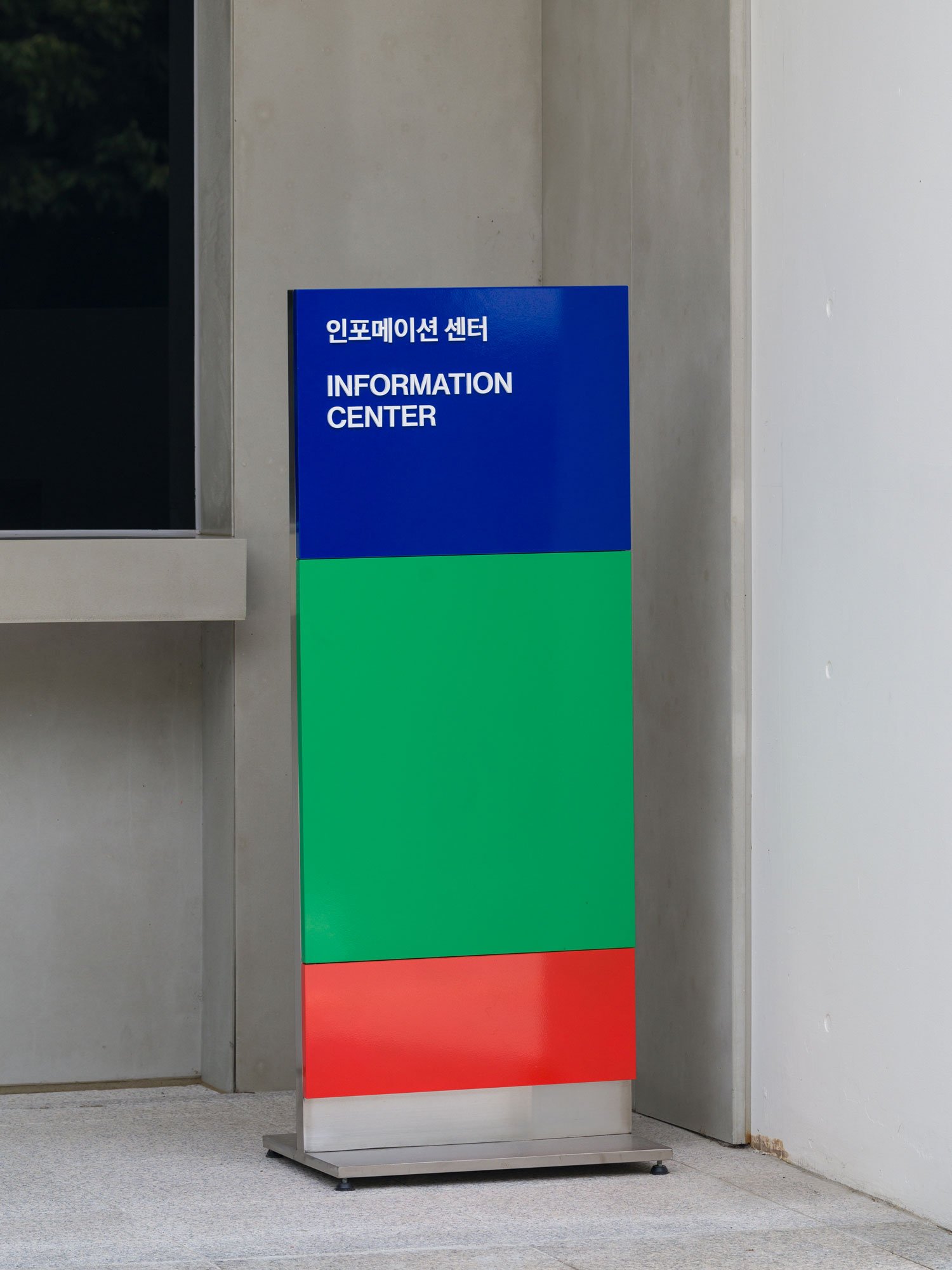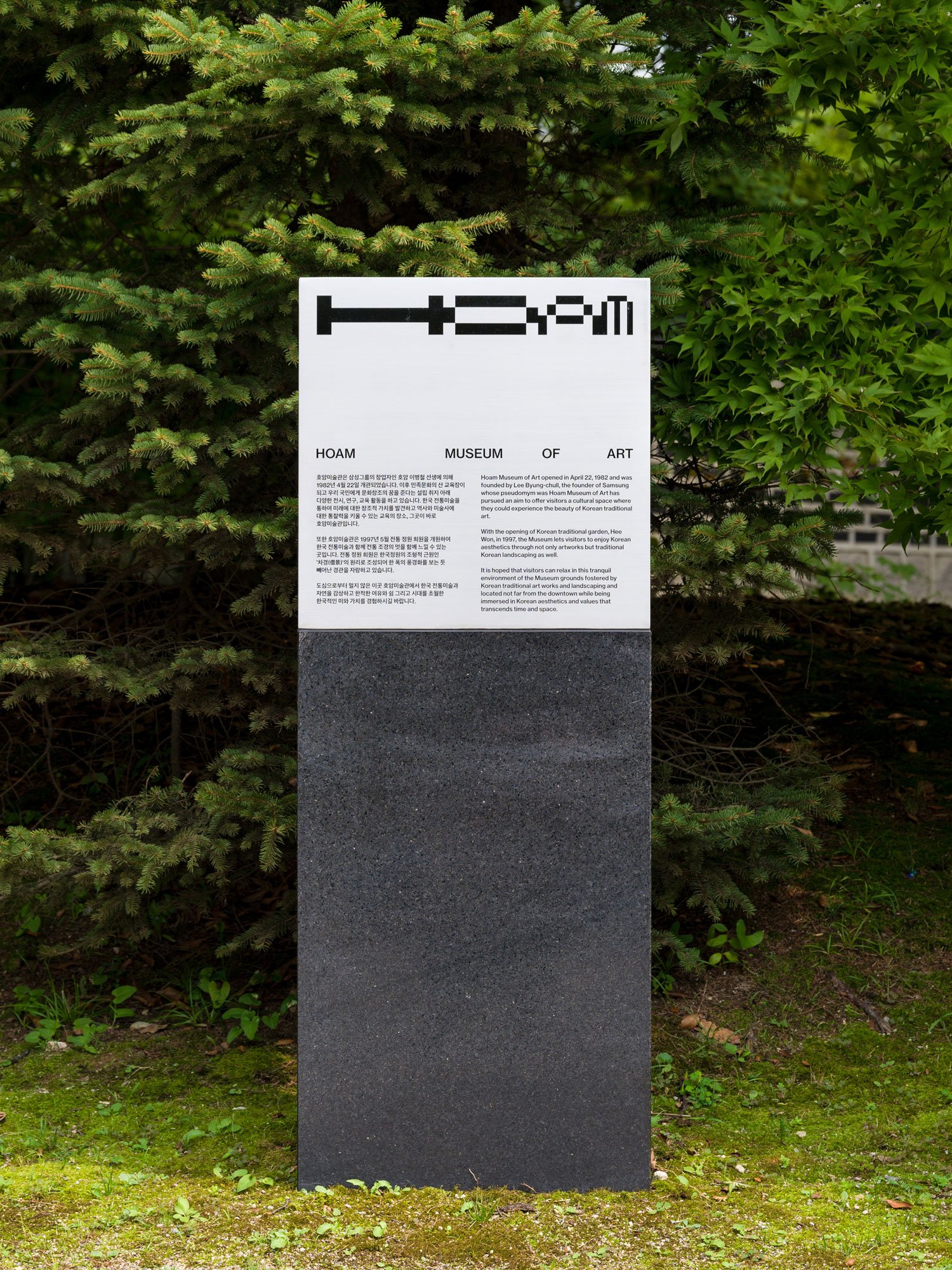
전통과 미래를 연결하는 계단, 호암미술관
호암미술관의 그래픽 아이덴티티, 로고 등을 포함한 MI(Museum Identity)의 새로운 디자인이 등장했다
전통과 미래를 연결하는 계단, 호암미술관
삼성그룹 창업자인 이병철 선생에 의해 1982년 4월 22일 개관된 호암미술관의 그래픽 아이덴티티, 로고 등을 포함한 MI(Museum Identity)의 새로운 디자인이 등장했다. 호암 미술관은 어린이에서 어른, 학생에서 전문가에 이르는 모든 관람객에게 문화예술을 통하여 미래에 대한 창조적 가치를 발견하고 역사와 예술에 관한 통찰력을 키울 수있는 교육의 장이 되는 것을 목표로 운영되어 온 미술관이다.
경기도 용인시에 위치한 호암 미술관은 이번 2023년 전통과 미래를 연결하는 계단을 상징하는 MI(Museum Identity)를 새롭게 디자인하였다. 이번 아이덴티티는 계단의 형상에서 모티브를 얻어 4:3:2:1의 비례 값에 바탕을 둔 조형으로 구성되었다. 이러한 비율은 순차적으로 쌓인 우리의 전통과 역사 그리고 점진적으로 나아가는 앞으로의 미래를 시사하도록 디자인되었다. MI의 형태는 3:2:1로 또는 4:3 등으로 다양한 매체나 상황에 따라 유연하게 적용할 수 있는 것이 특징이다.
이번 프로젝트를 통해 호암 미술관은 로고부터 사이니지까지 미술관 전체를 일관된 양식으로 시각적 정체성을 세웠다. 상향과 하향, 양방향으로 통하는 계단과 같이 호암미술관을 통해 우리는 시대를 초월한 가치 즉, 전통과 역사를 전승하며 그 가치를 배우는 동시에 미래에 대한 새로운 생각을 꿈꿀 수 있게 디자인된 MI를 확인해볼 수 있다. 더 많은 자료는 호암 미술관 웹사이트와 오디너리피플 웹사이트에서 확인할 수 있다.